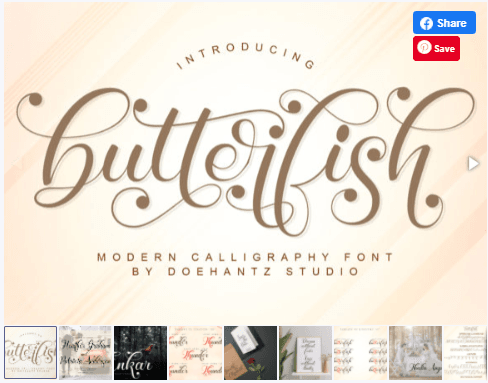
Butterfish Font
Butterfish - это романтичный и сладкий каллиграфический шрифт с персонажами, которые танцуют вдоль базовой линии. Он придаст изюминку любому дизайнерскому проекту, который вы желаете создать! Этот шрифт имеет кодировку PUA, что означает, что вы можете легко получить доступ ко всем удивительным глифам и лигатурам!